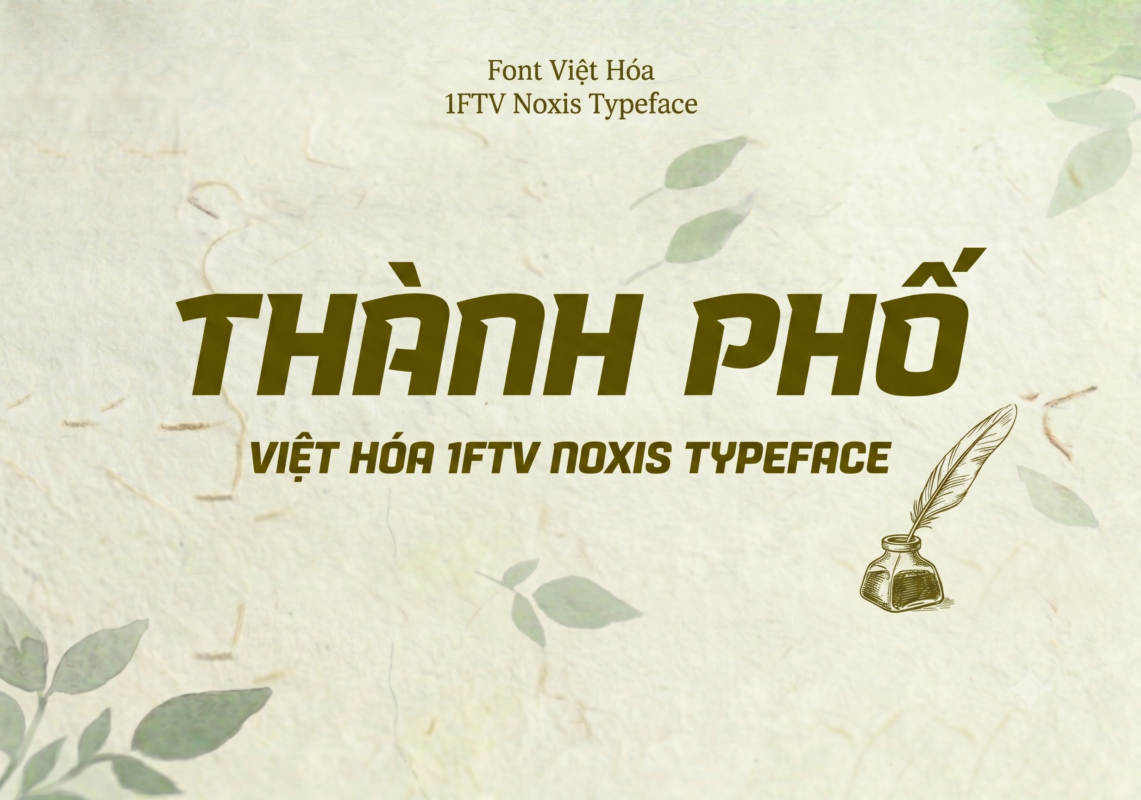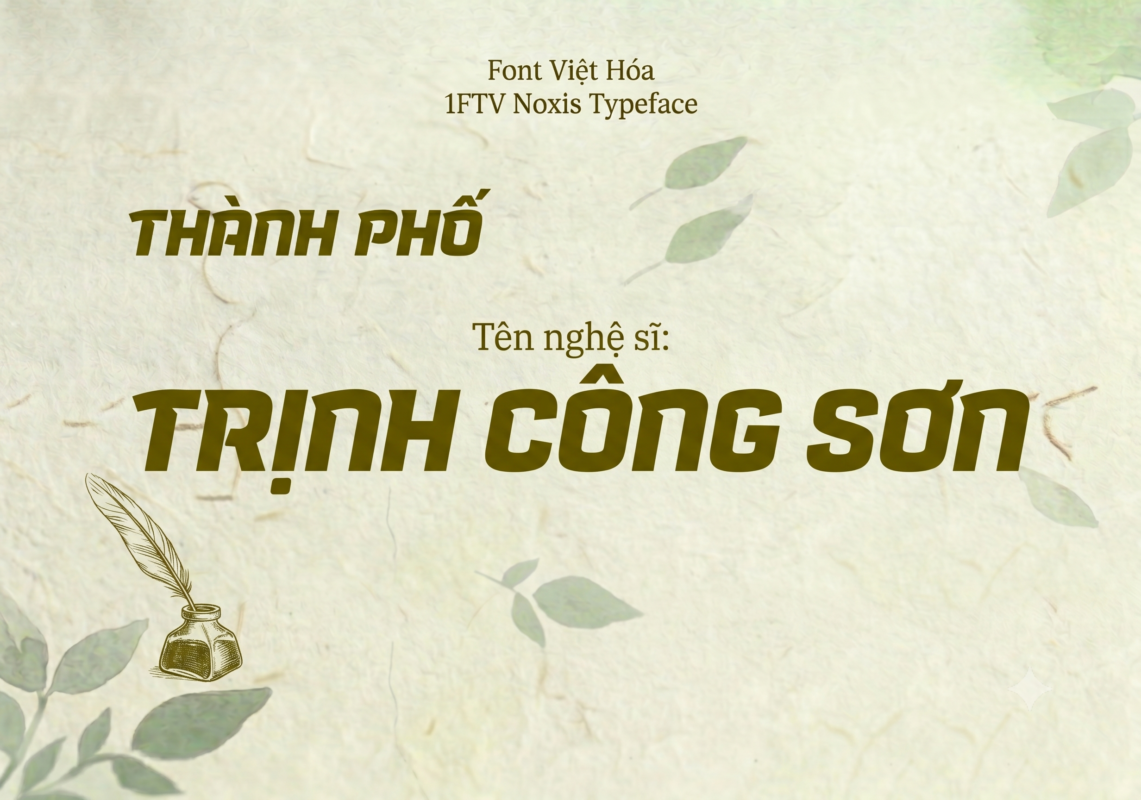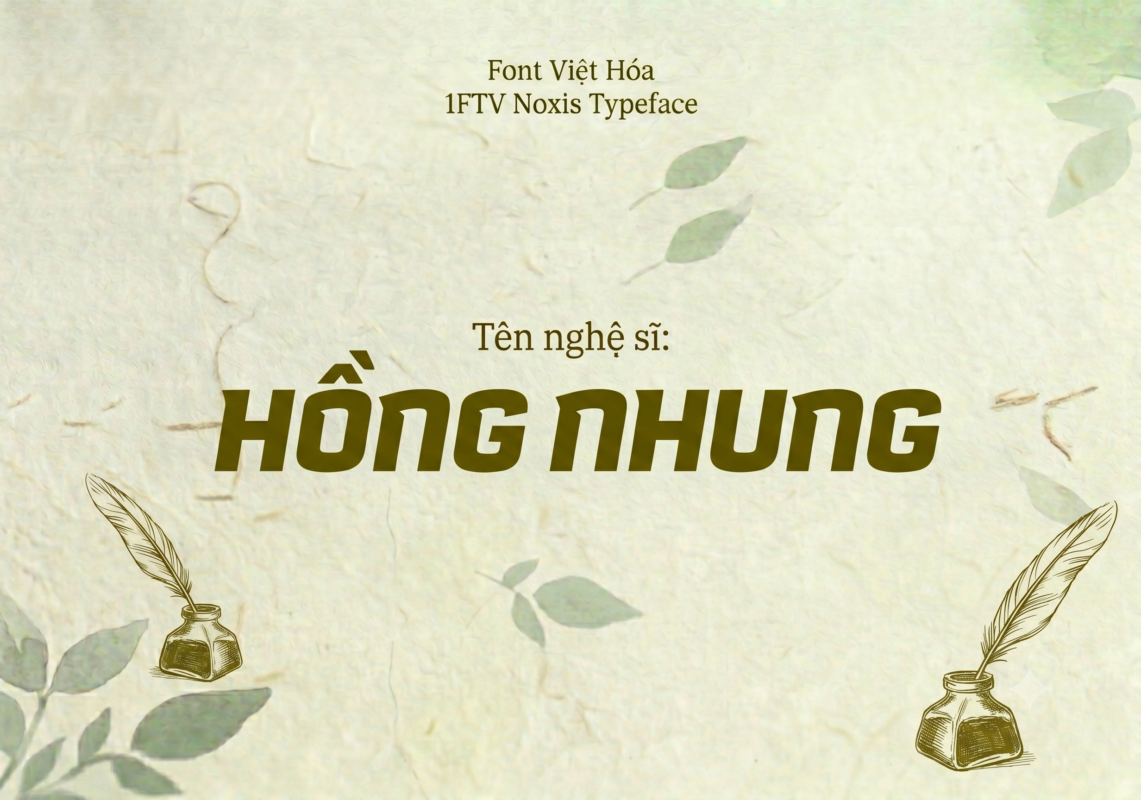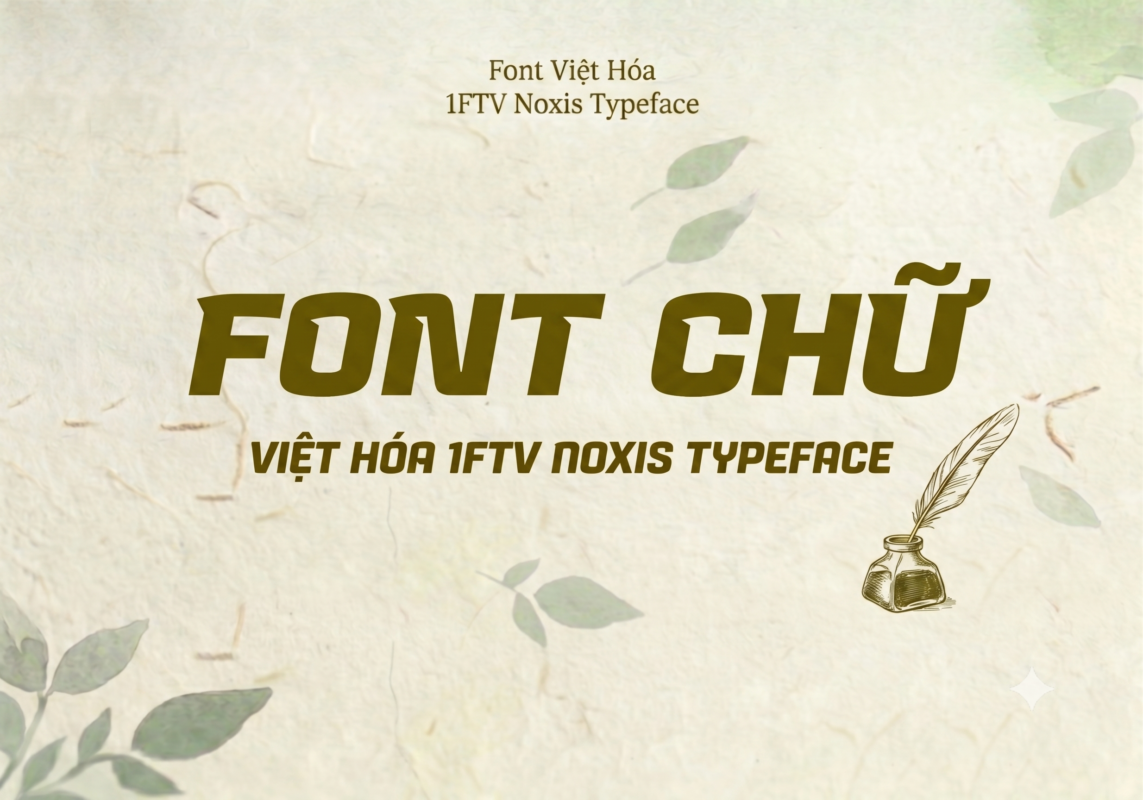
1FTV Noxis
Bên cạnh những kiểu chữ retro hoài cổ hay những nét chữ viết tay mềm mại, xu hướng thiết kế hiện đại luôn đòi hỏi những phông chữ mang tính bứt phá, mạnh mẽ và đậm chất công nghệ. Nếu bạn đang tìm kiếm một làn gió mới để làm nổi bật tiêu đề video, thiết kế các banner gaming hay các sản phẩm truyền thông thể thao tốc độ, thì font 1FTV Noxis chính là câu trả lời hoàn hảo.
Đây là một công cụ đắc lực giúp các nhà sáng tạo nội dung và các nhà thiết kế đồ họa tối ưu hóa hiệu ứng thị giác. Phông chữ này cực kỳ thích hợp để làm tiêu đề nổi bật cho thumbnail Youtube, video ngắn trên Tiktok, Reels hoặc các thiết kế quảng cáo cần sự mạnh mẽ, cá tính. Với cấu trúc nghiêng động và các đường cắt góc sắc sảo, font 1FTV Noxis hứa hẹn sẽ mang lại sự lôi cuốn đặc biệt ngay từ cái nhìn đầu tiên.
Giới thiệu về font 1FTV Noxis
Font 1FTV Noxis là một phông chữ display (hiển thị) không chân mang đậm tinh thần hiện đại, giả tưởng và công nghệ tương lai. Kiểu chữ này được thiết kế và phát triển thông qua công cụ Fontself Maker phiên bản 3.5.9, mang lại sự chuẩn xác cao trong từng đường nét.
Phiên bản xuất hiện trong bài viết này sở hữu định dạng opentype layout tiên tiến, đi kèm chứng thực kỹ thuật số (digitally signed) và cấu trúc đường nét chuẩn postscript outlines. Điều này giúp phông chữ hiển thị sắc nét tuyệt đối, không bị nhòe hay vỡ hình khi bạn co giãn kích thước trên các nền tảng kỹ thuật số hoặc in ấn khổ lớn. Được chia sẻ bởi đội ngũ 1FTV, đây là giải pháp tối ưu cho cộng đồng thiết kế đồ họa và biên tập video tại Việt Nam.
Đặc điểm nổi bật của phong cách thiết kế Noxis
Sức hút khác biệt của font 1FTV Noxis đến từ cấu trúc chữ nghiêng (italic) tràn đầy năng lượng và các góc cắt hình học táo bạo. Các ký tự như O, D, B, R không bo góc tròn trịa thông thường mà được vát cạnh dứt khoát bên trong, mô phỏng phong cách thiết kế của các tựa game khoa học viễn tưởng, cyberpunk hoặc các giải đua xe tốc độ.
Phông chữ được định dạng theo cấu trúc all-caps (viết hoa toàn bộ), tạo nên sự cân bằng, gọn gàng và đồng đều tuyệt đối về mặt bố cục khi sắp xếp các cụm chữ cạnh nhau. Độ dày nét của font chữ thuộc hàng siêu đậm (bold), giúp phần văn bản của bạn luôn nổi bật lên hẳn so với các chi tiết nền phức tạp xung quanh, tăng cường tối đa khả năng nhận diện thị giác.
Hệ thống khoảng cách giữa các chữ (kerning) và độ giãn dòng (tracking) được căn chỉnh vô cùng chuẩn xác, giúp các chữ cái khi đứng cạnh nhau luôn giữ được khoảng hở thẩm mỹ, không bị dính nét hay gây cảm giác rối mắt. Bên cạnh bộ chữ cái viết hoa đồng bộ, phông chữ còn tích hợp đầy đủ dãy số từ 0-9 và các ký tự đặc biệt, dấu câu cơ bản (.,;:''"(!?)+-*/-), hỗ trợ bạn thoải mái sáng tạo nội dung mà không lo lỗi hiển thị.
Hình ảnh demo thực tế của font 1FTV Noxis
Để giúp bạn dễ dàng hình dung độ sắc nét và tính tương thích của phông chữ này trên các kích thước hiển thị khác nhau, hãy xem qua bảng mô phỏng từ size nhỏ đến lớn:
Kích thước nhỏ (12pt – 24pt): Các nét chữ đậm và góc nghiêng vẫn hiển thị rõ ràng, form chữ vững chãi, dễ đọc.
Kích thước lớn (36pt – 72pt): Thể hiện trọn vẹn sức mạnh của các đường cắt hình khối, tạo hiệu ứng đè nặng thị giác (visual impact) cực kỳ mạnh mẽ, lý tưởng để làm các câu giật tít thu hút người xem.
Ứng dụng của font Noxis trong thiết kế đồ họa và làm video
Sở hữu nét cá tính và năng động độc nhất, font 1FTV Noxis mở ra không gian sáng tạo rộng lớn cho các dự án truyền thông, marketing:
Thiết kế thumbnail và ảnh thu nhỏ: Đây là vũ khí tối thượng cho các thumbnail Youtube, Tiktok thuộc chủ đề gaming, công nghệ, review xe hoặc thể thao. Khi kết hợp với các tông màu tương phản mạnh như vàng, neon, đỏ trên nền tối, tiêu đề sẽ vô cùng kích thích người xem bấm vào.
Làm tiêu đề video ngắn (Shorts, Reels, Tiktok): Cấu trúc chữ nghiêng mạnh mẽ này giúp các câu key-word, tiêu đề mở đầu video trở nên nổi bật và giữ chân người xem lướt chậm lại.
Banner và poster quảng cáo: Thích hợp cho các poster giải đấu thể thao điện tử (esports), banner giới thiệu sản phẩm công nghệ hoặc các chương trình sự kiện hành động.
Nhận diện thương hiệu phong cách đường phố: Phù hợp làm logo dạng chữ khối cho các thương hiệu thời trang streetwear, phòng gym, hoặc các câu lạc bộ thể thao năng động.